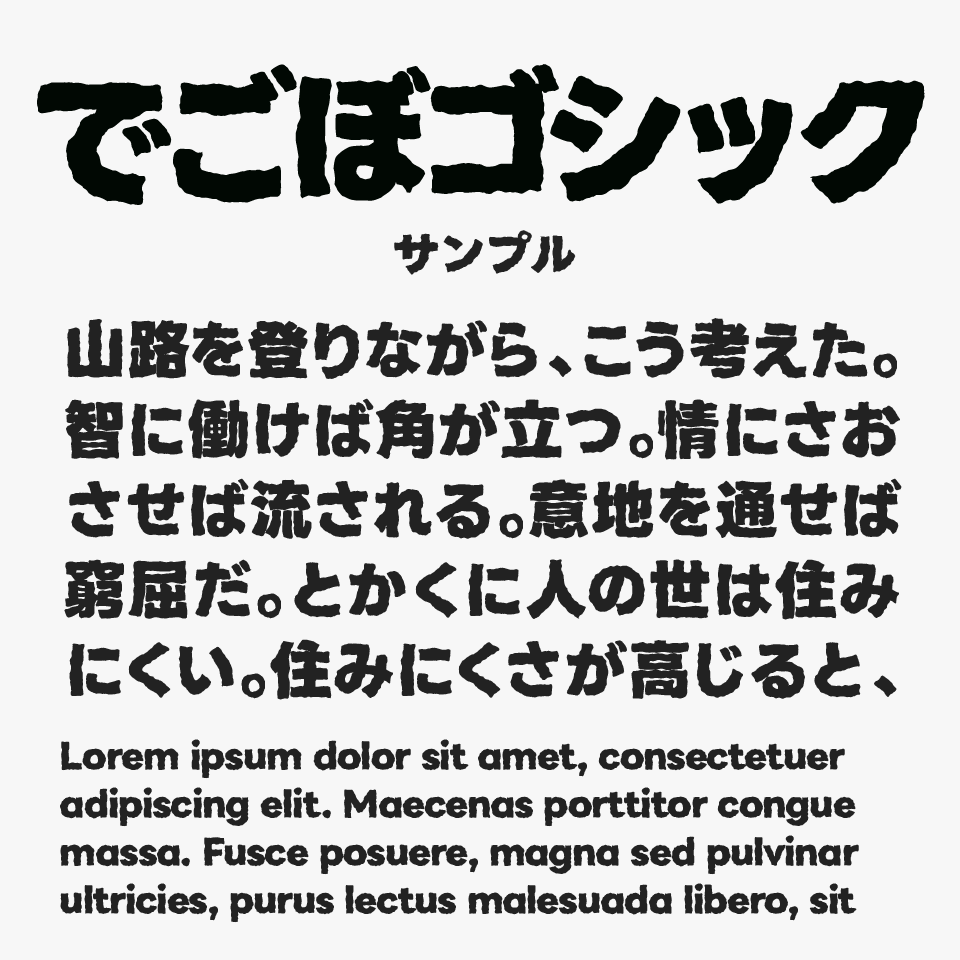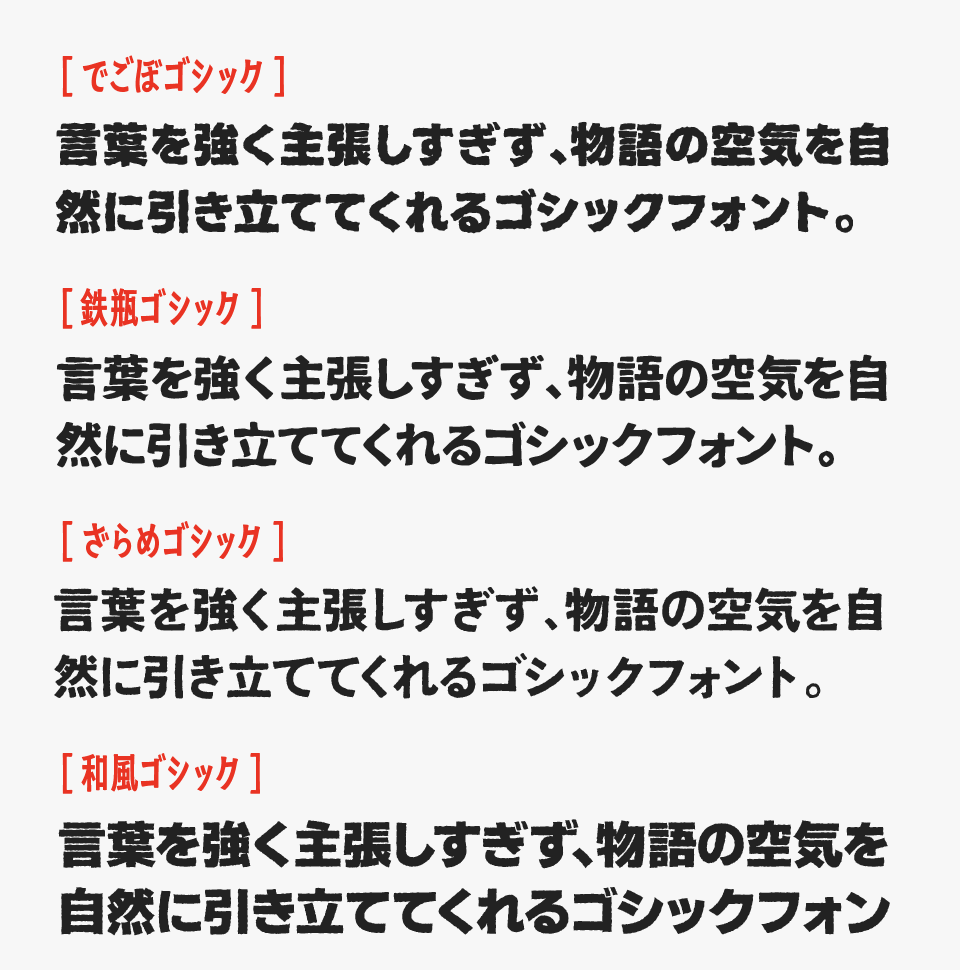
でごぼゴシックフォントは、「LINE Seed」フォントのどっしりとした極太ゴシック体をベースに、文字の輪郭へランダムな凹凸やザラつきを加えた、無骨で力強さのあるゴシック体フォントです。
ラフな質感が加わることで、工業製品や金属、岩肌を思わせる重厚感が感じられるフォントです。LINE Seedをベースとしているので大胆なシルエットでありながら視認性も高く、タイトルや見出しでもしっかりとインパクトを残せるデザインフォントです。
アウトドアやクラフト、工業・DIYをテーマにしたデザインはもちろん、レトロゲームや漫画のタイトル、インパクト重視のサムネイルなどにもぴったりなフォントです。
でこぼゴシック
でごぼゴシックフォントを、ほかのぼこぼこ・ざらざらとした質感を持つフォントと比較してみると、不規則な凹凸によるクラフト感と、ゴシック体ならではの読みやすさを両立しているところが特に魅力のあるフォントです。
比較フォントは、「鉄瓶ゴシック」「ざらめゴシック」「和風ゴシック」を使用していますが、どれも特徴的な質感がユニークなゴシックフォントなので、ぜひあわせてチェックしてみてください。
でこぼゴシックと、「鉄瓶ゴシック」「ざらめゴシック」「和風ゴシック」を比較